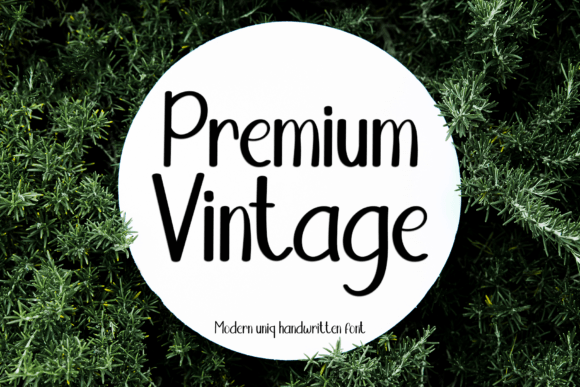
Premium Vintage
Việc tìm kiếm các thành phần thiết kế phù hợp có thể là một thách thức, nhưng Premium Vintage cung cấp một bộ sưu tập đặc biệt giúp nâng tầm công việc của bạn ngay lập tức.
Được chế tác với độ chính xác cao, Premium Vintage cung cấp các vector sạch, kiểu chữ mượt mà và giấy phép thương mại để bạn yên tâm.
Cho dù bạn đang tạo sản phẩm POD (In theo yêu cầu), thiệp mời đám cưới hay đồ họa mạng xã hội, Premium Vintage đều là một sự lựa chọn lý tưởng.